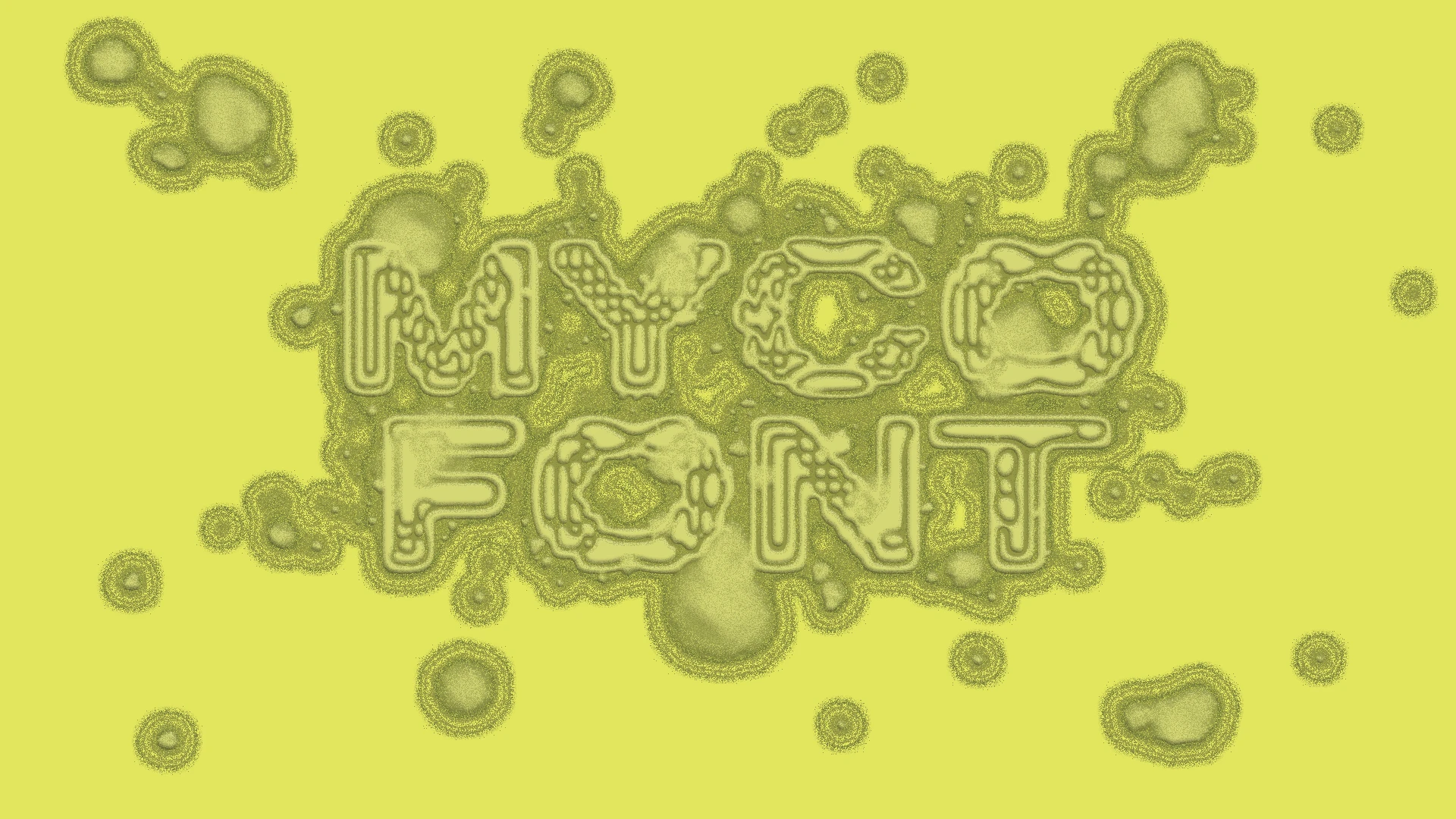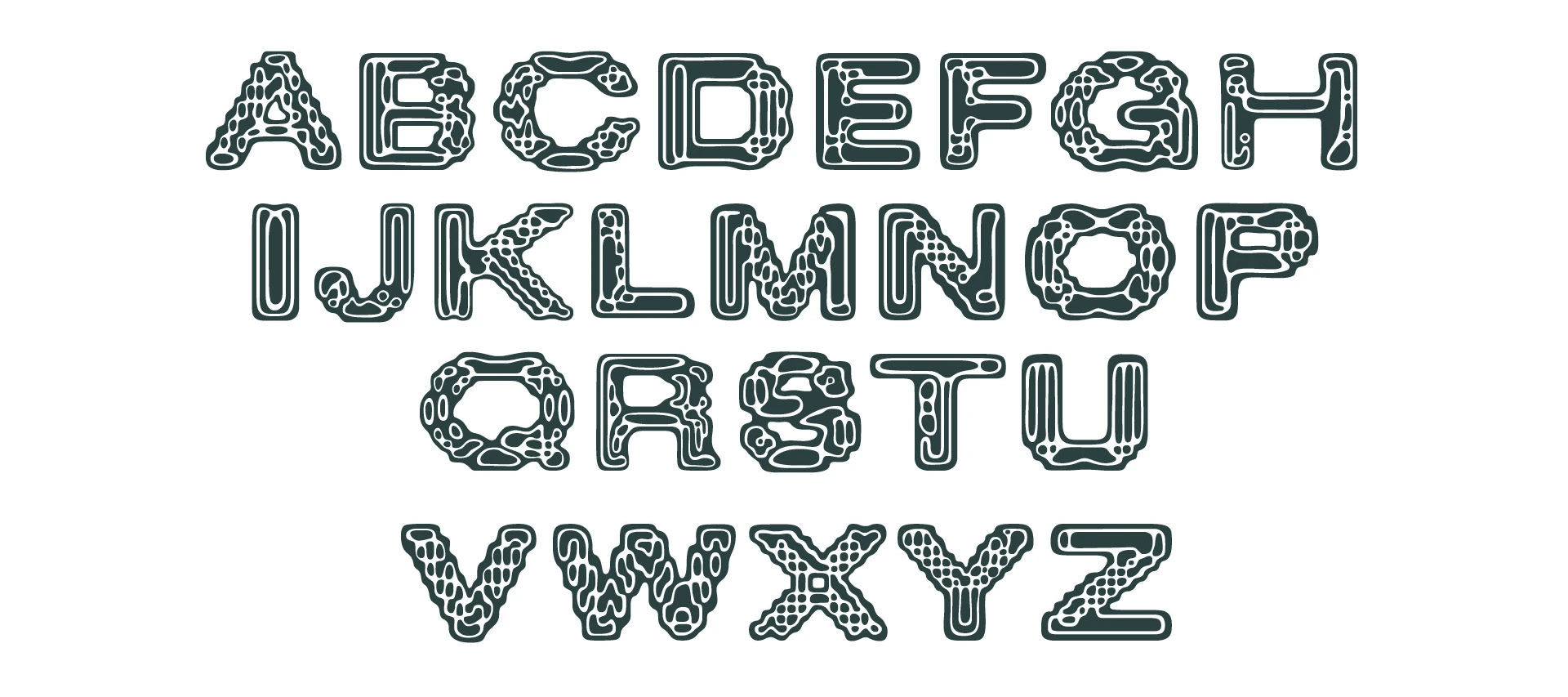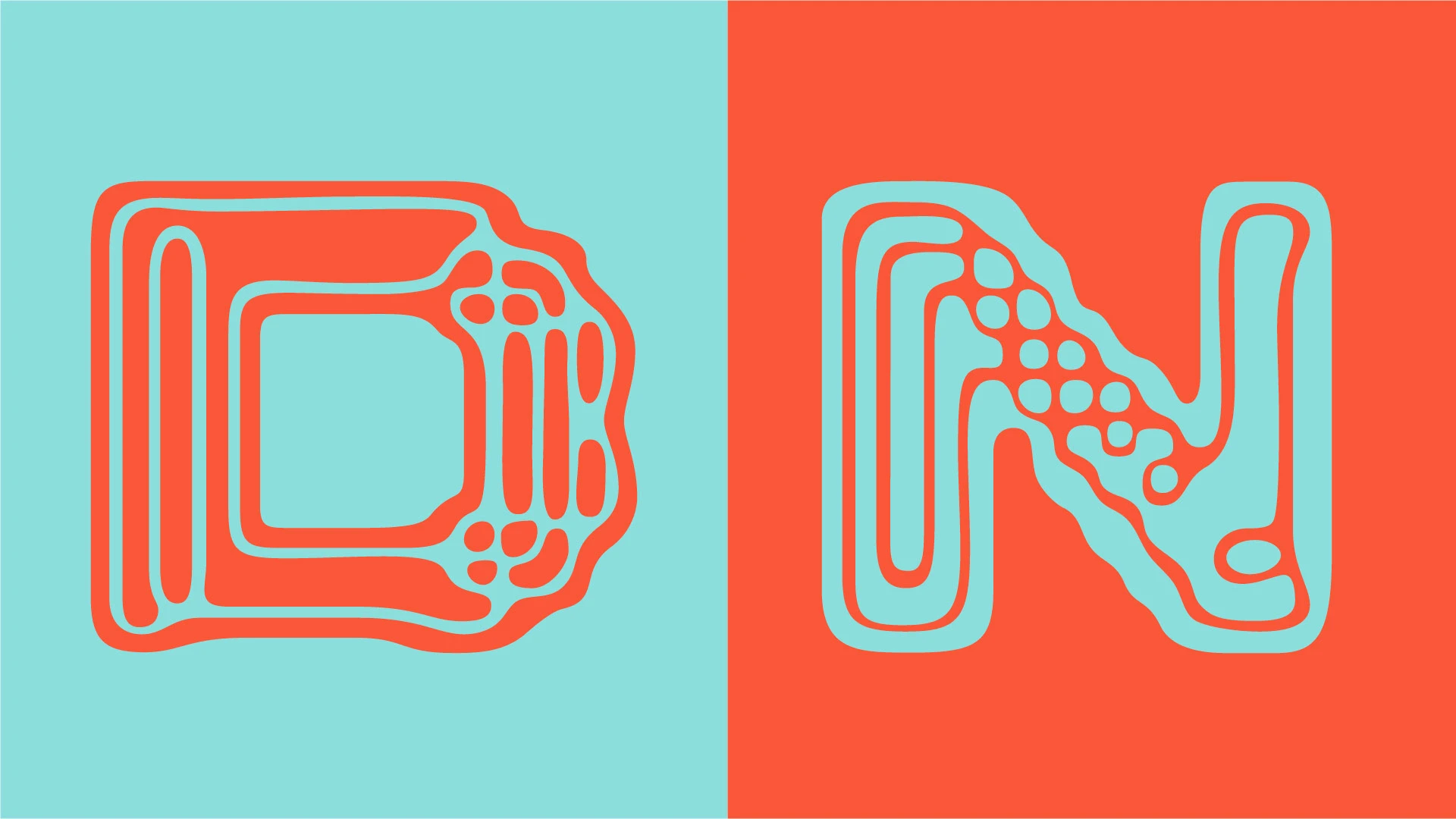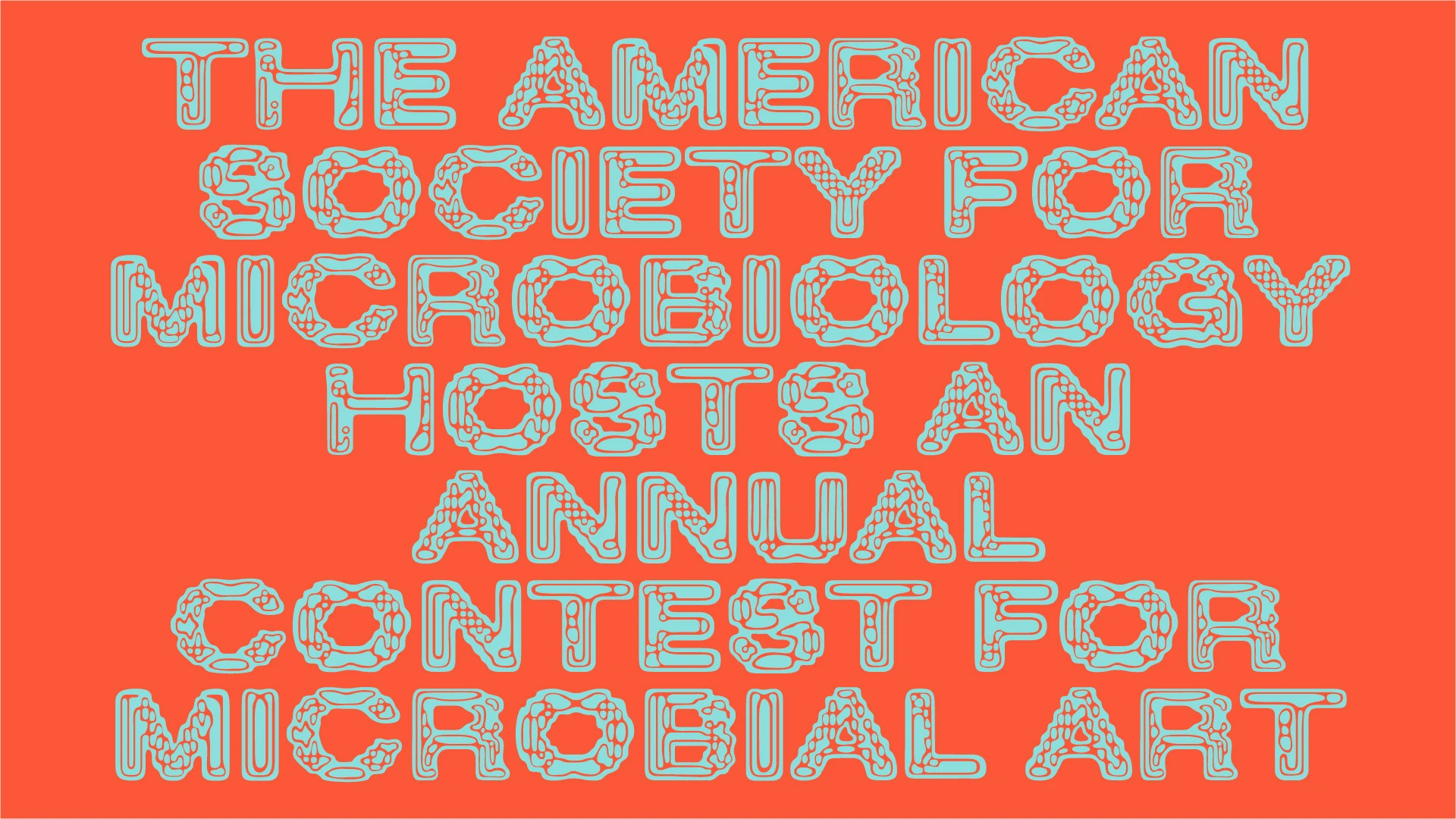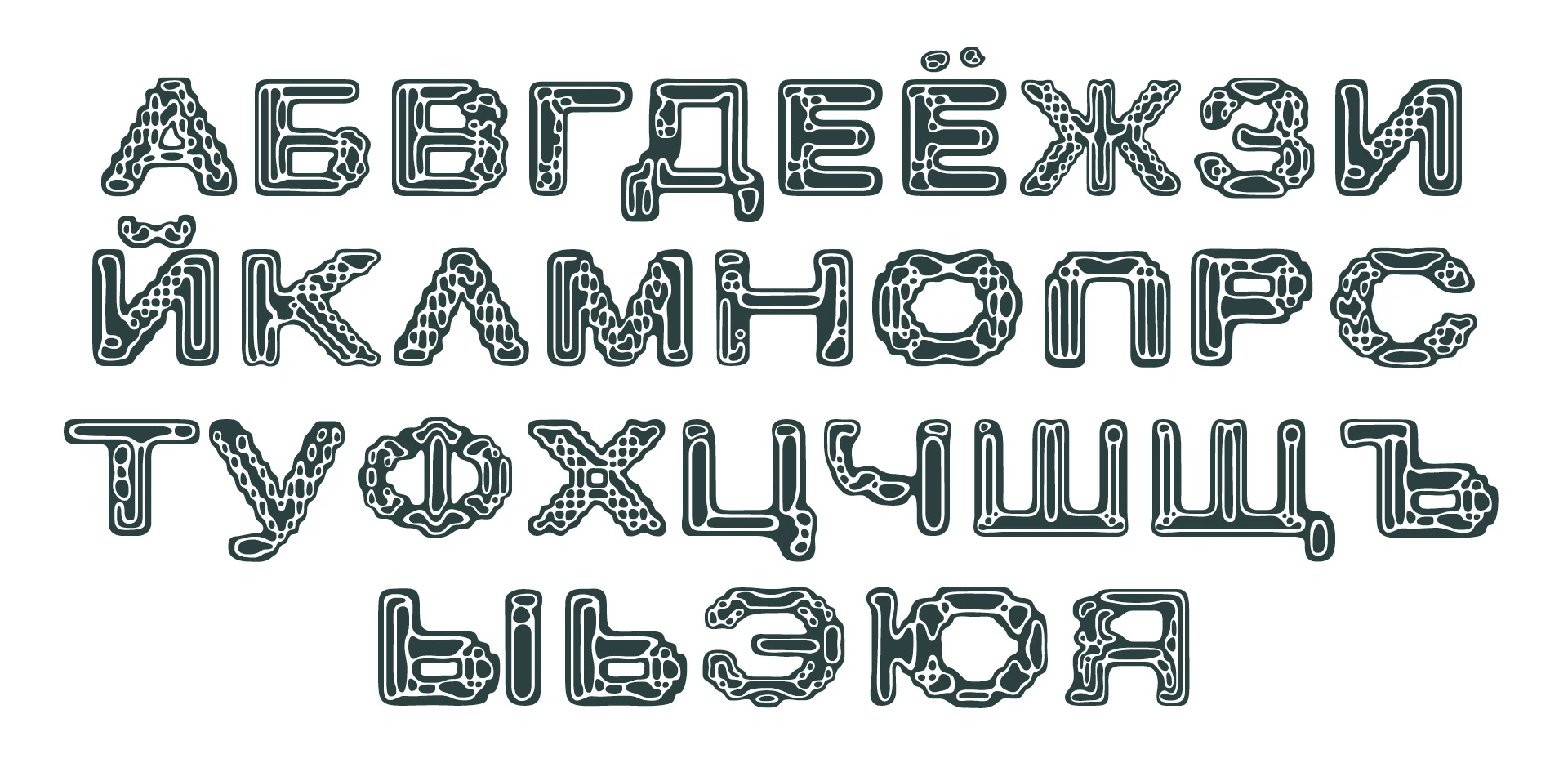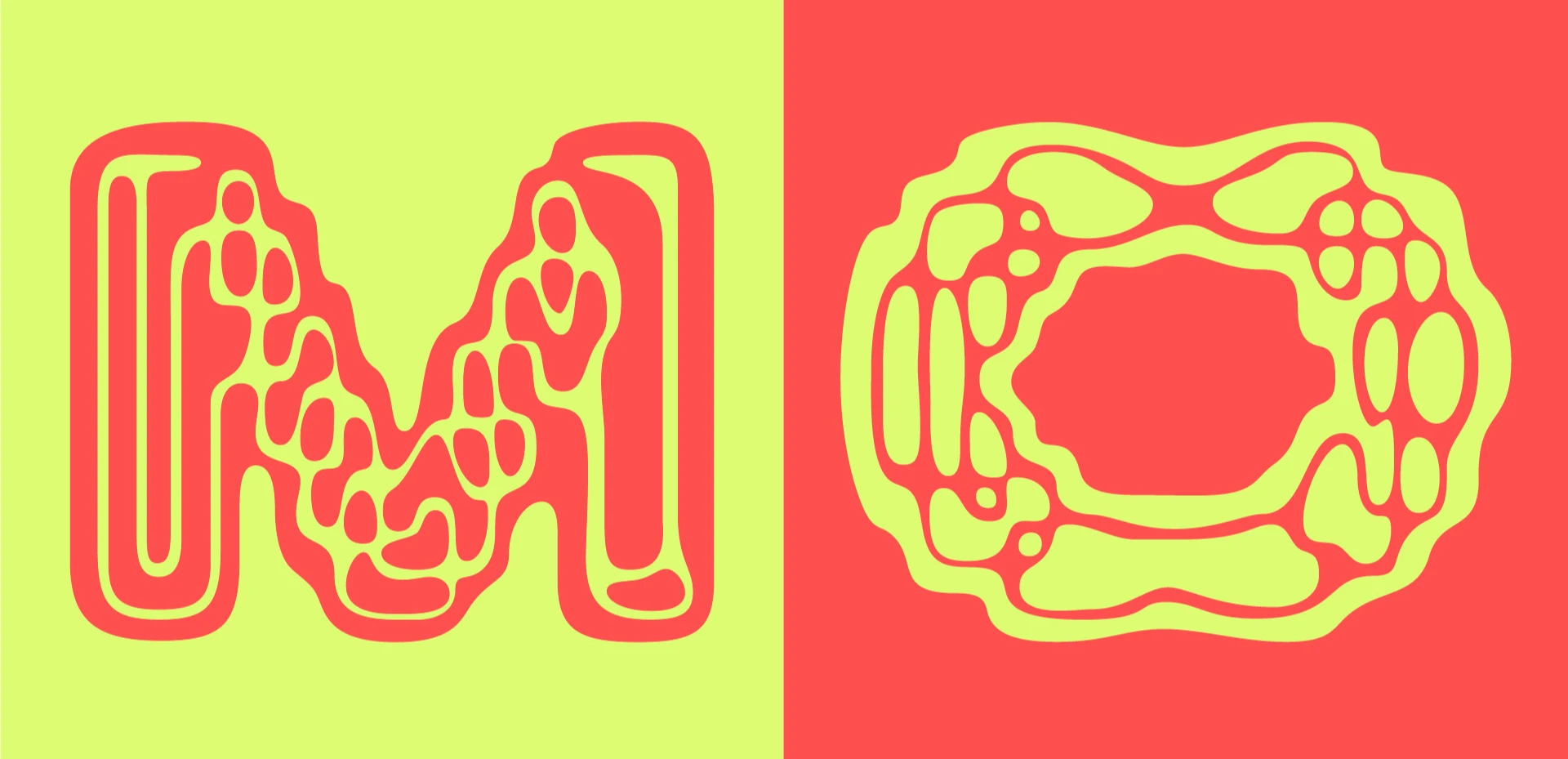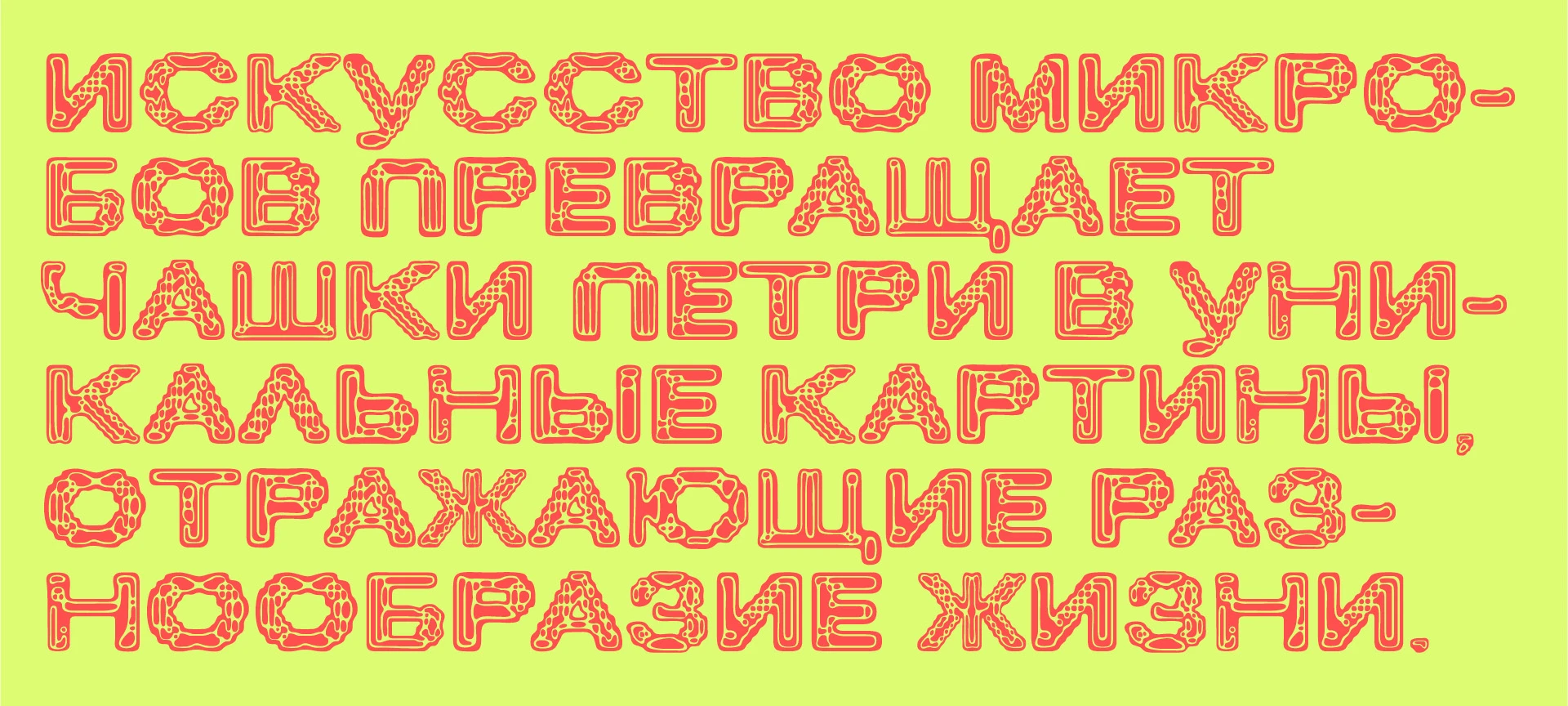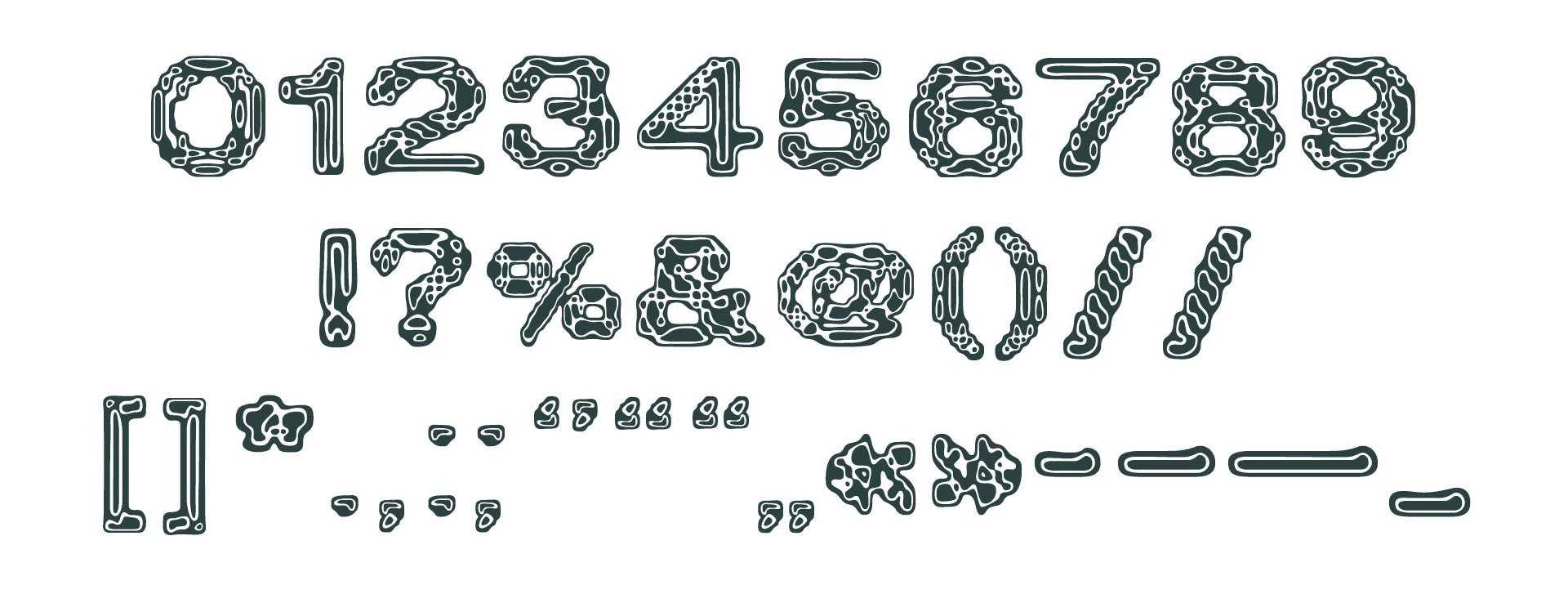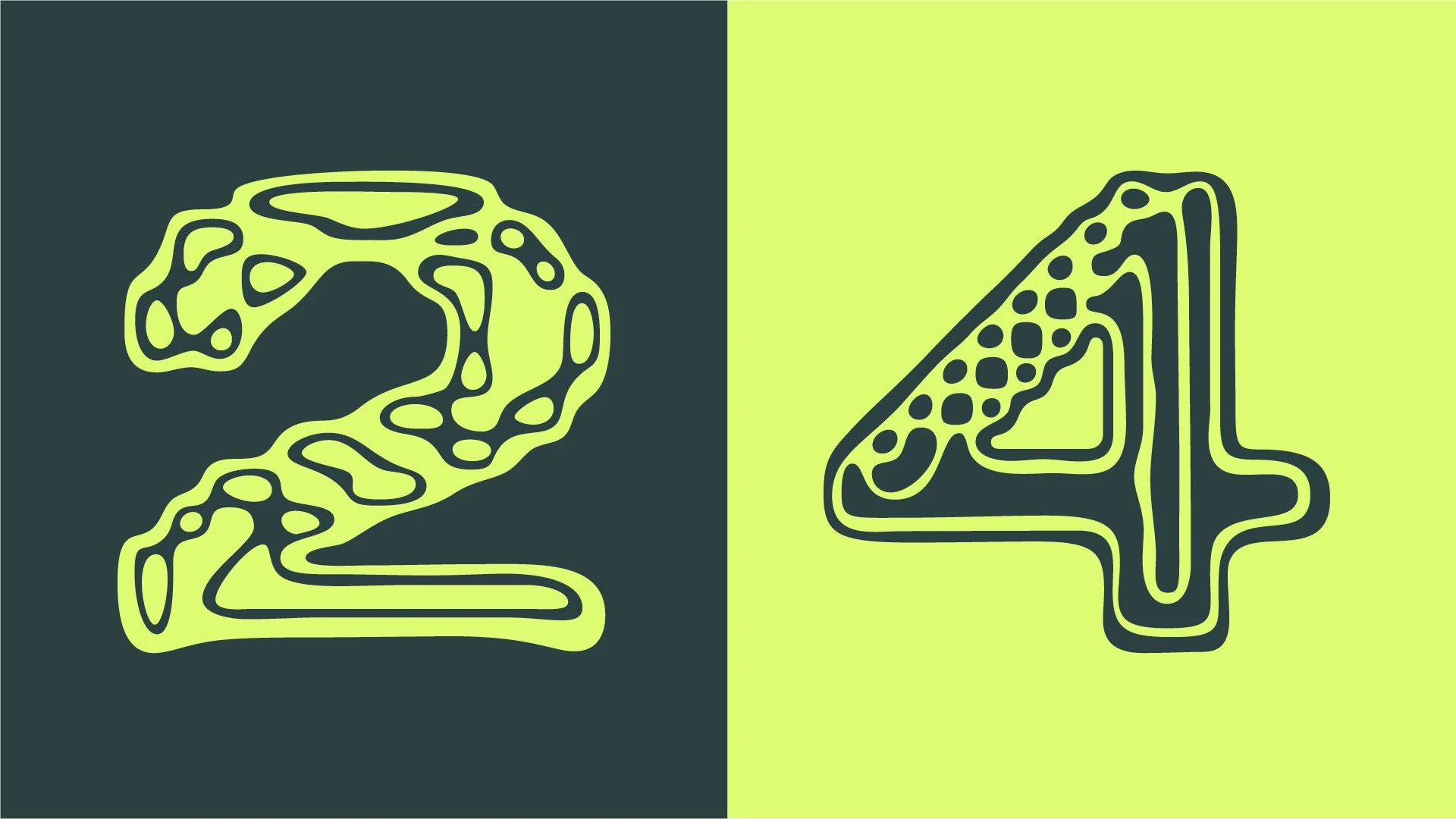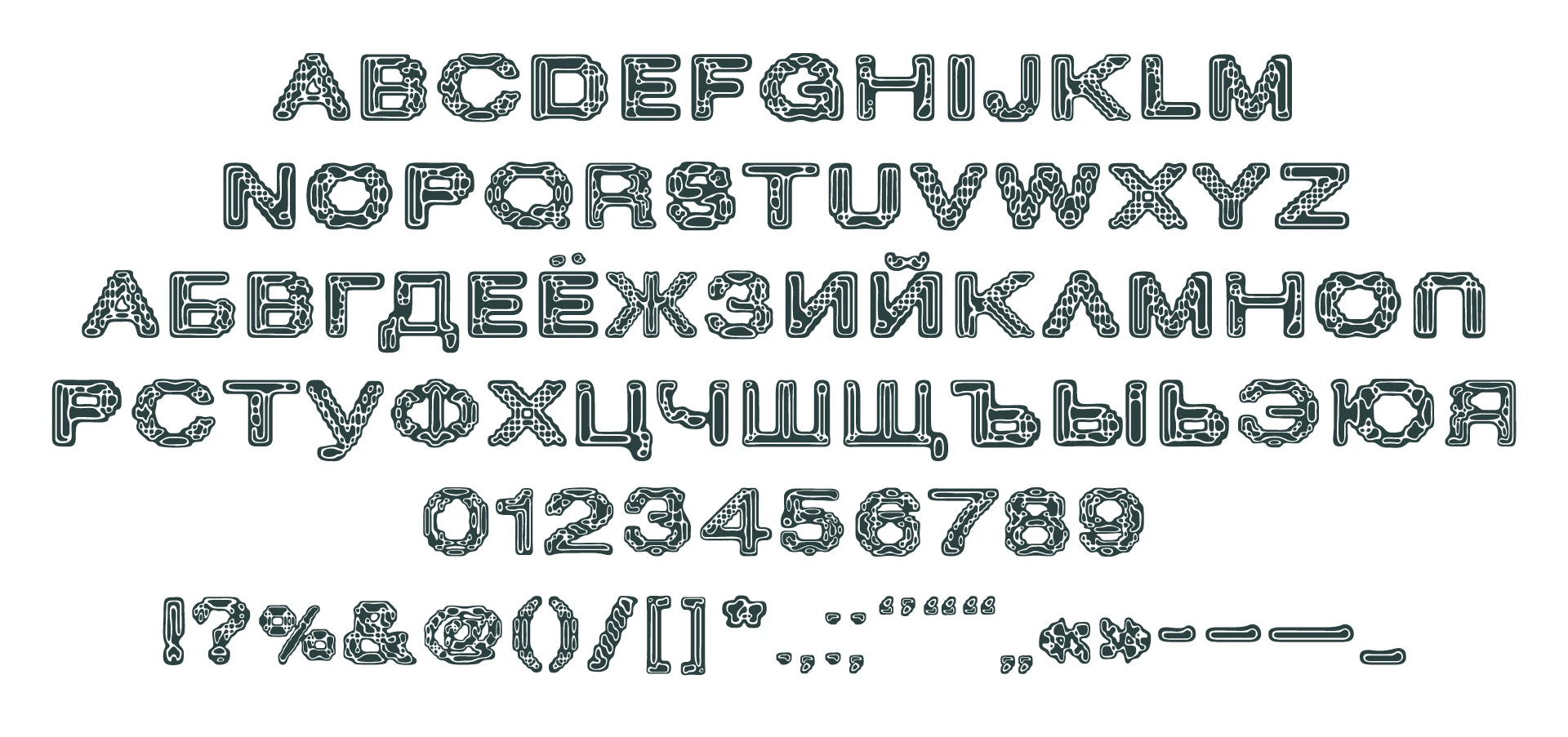
MYCO FONT
MYCO is a display type inspired by agar art, where microbiology meets visual creativity.
It reflects the process of cultivating bacteria on agar in Petri dishes, transforming scientific experiments into unique artistic forms.
MYCO — акцидентный шрифт, вдохновленный агарным искусством, где микробиология встречается с визуальным творчеством. Он отражает процесс культивирования бактерий на агар-агаре в чашках Петри, превращая научные эксперименты в уникальные художественные формы.